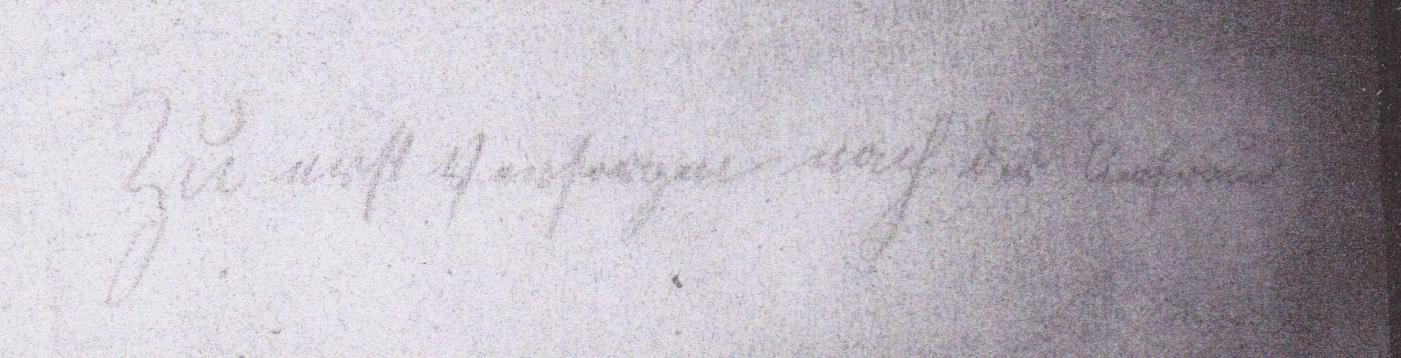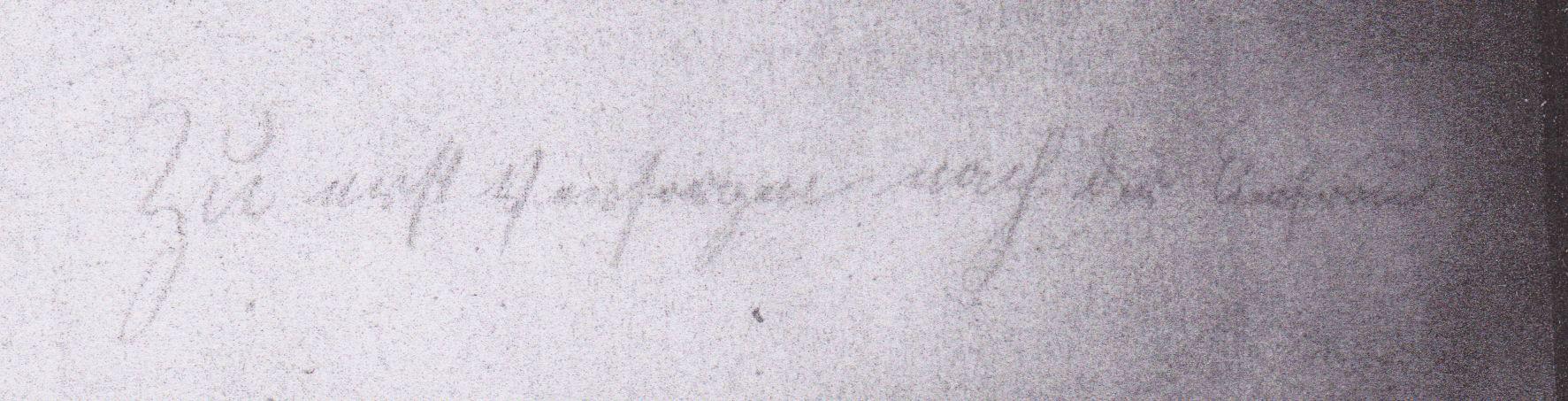
Handschriftlicher Text in Kurrent
ich habe von einem Bekannten aus Frankreich ein Aufnahme zugesandt bekommen, worauf ein Text ist, der auf der Rückseite eines Gemäldes geschrieben war.
Ich habe mich um die Entzifferung des Textes auch schon versucht, bin mir aber nicht sicher, ob meine Übersetzung richtig ist. Nun bitte ich Euch um Hilfe, ob jemand den Text richtig lesen kann.
Ich glaube, "Nachfragen" passt nicht zum Schriftbild. Ich sehe beim ersten Buchstaben einen Kringel rechts unten; das deutet auf ein "v". Die folgenden Buchstaben können kein "ch" sein (siehe nächstes Wort "nach"); ich sehe eher ein "er". Und der "lange" Buchstabe ist wohl eher ein "s" als ein "f". Also vielleicht "versorgen"?
Beim letzten Wort habe ich leider keine gute Idee. Beim ersten Betrachten meinte ich einen Kringel über den Buchstaben zu sehen, was auf ein "u" hindeuten würde. Ist aber vielleicht eine Täuschung. "Einfahrt" kann es nicht sein, dafür fehlt das charakteristische "h" mit Schlaufenunterlänge.
Gibt es weitere Infos zum Gemälde oder zu den Umständen der Beschriftung? Vielleicht kommen wir so auf die Lösung.
hier der Text von meinem Bekannten und ein Screenshot des mitgeschickten Bildes:
Here is a copy of the Christmas crib. The inscription that I sent you is in the back of it.
In front there is another small one: Josep Barth, Munchen  1875.
"Lieferung"
Das L ist ein wenig unorthodox
Könnte auch ein C sein, außerdem scheint mir vorm f in spe mehr als ie und den Unterschwung des g vermisse ich, aber eigentlich ist in dem Bereich des Bildes die Qualität a weng zu schlecht, geht die Ecke nochmal besser beleuchtet?